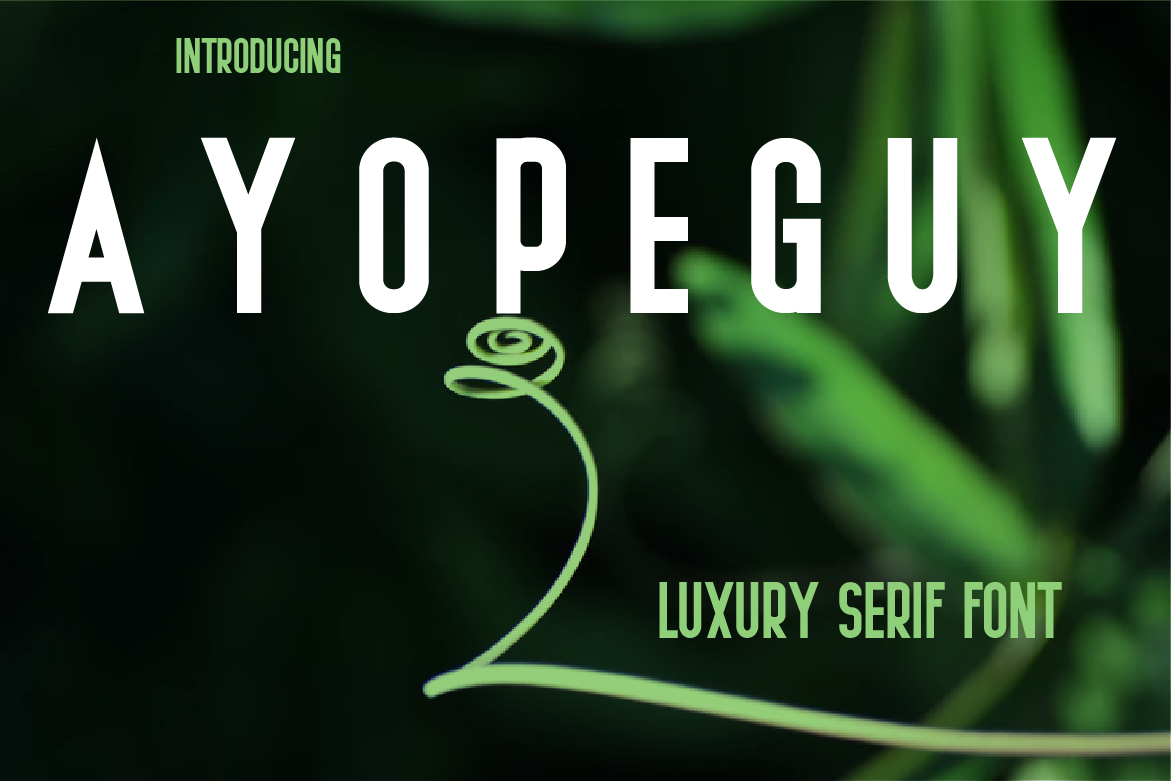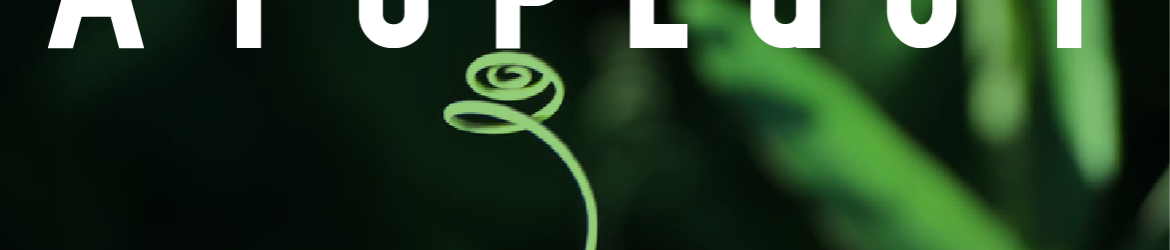
A AYOPEGUY Font é uma serif font que captura a essência forte e robusta do tipo sans-serif, oferecendo uma forma sólida e firme com linhas equilibradas. Combinando elementos de serif no design, ela traz um toque de elegância e sofisticação sem perder a força imponente característica. Perfeita para aplicar em materiais que precisam de um aspecto moderno mas profundo, AYOPEGUY é uma escolha ideal para designers que valorizam tanto o poder da leitura quanto o impacto visual. Se você procura por uma fonte com estilo próprio, que não apenas ressalta no design gráfico como também se integra perfeitamente em qualquer layout editorial ou publicitário, AYOPEGUY pode ser a solução perfeita para suas necessidades.